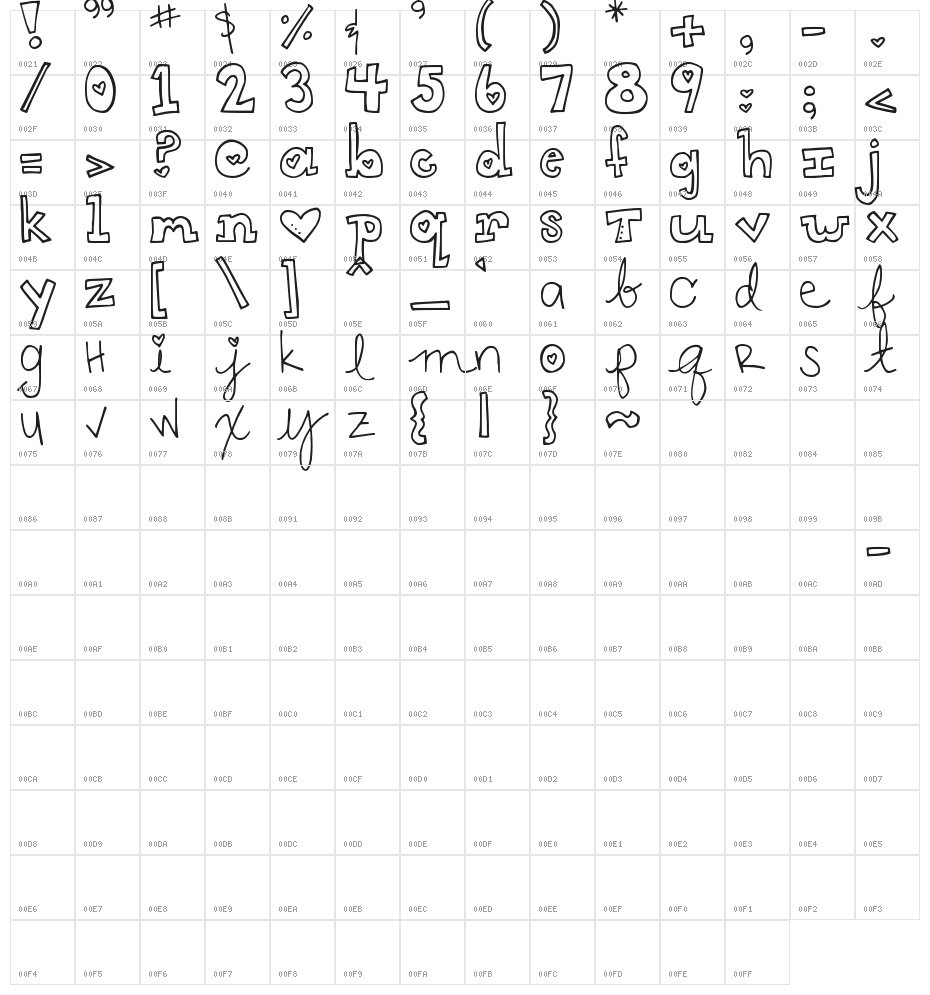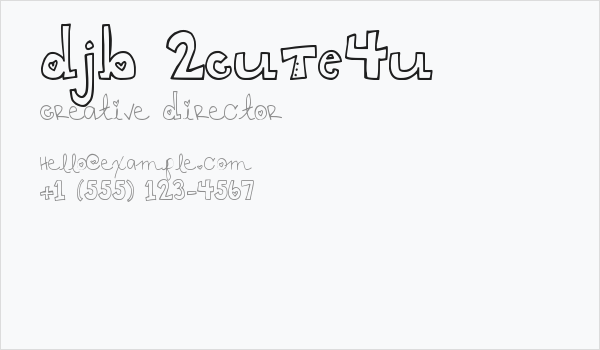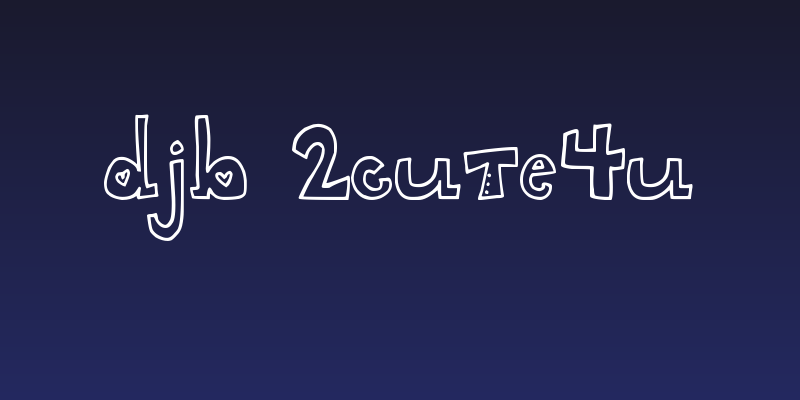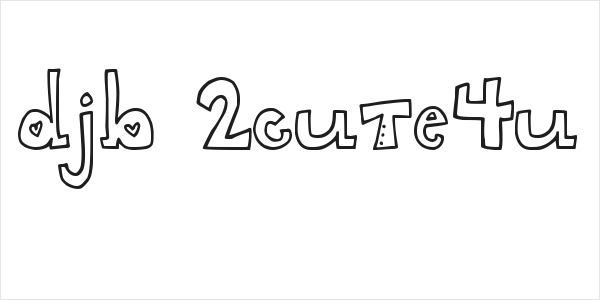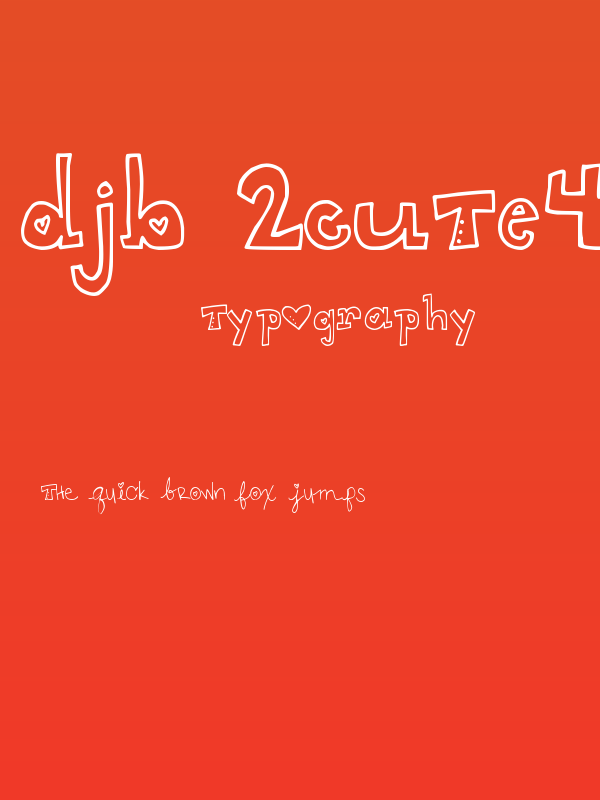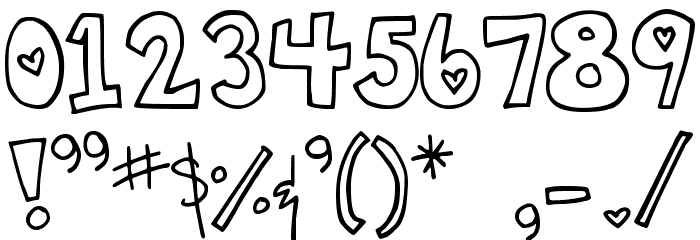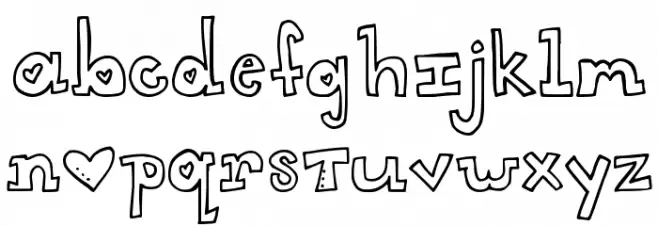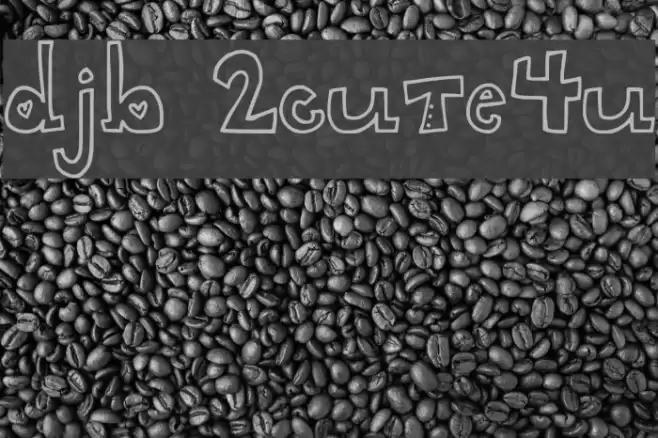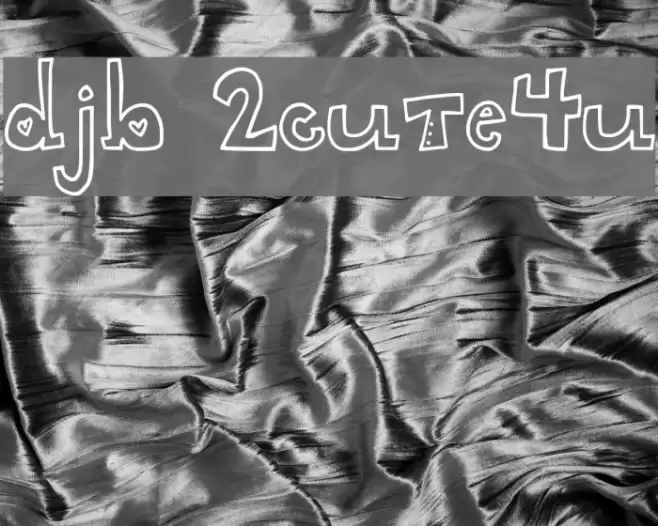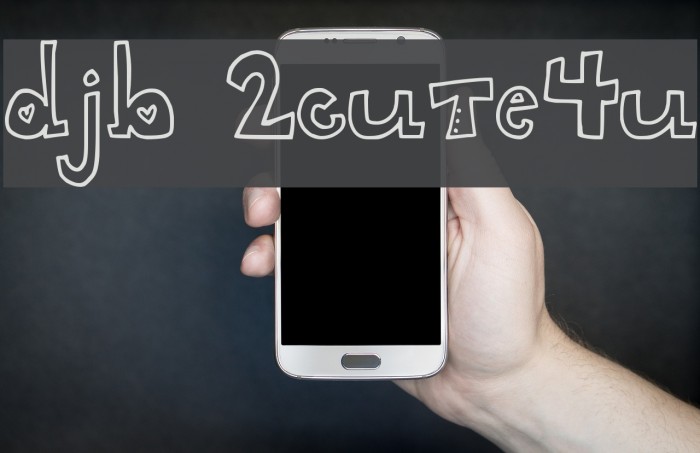
DJB 2CUTE4U Font
| Stile generale | Playful, Whimsical |
| Caso d'uso | Headlines, Logos, Decorative Text |
| Progetti proposti | Ideal for children's books, greeting cards, playful branding, and social media graphics. |